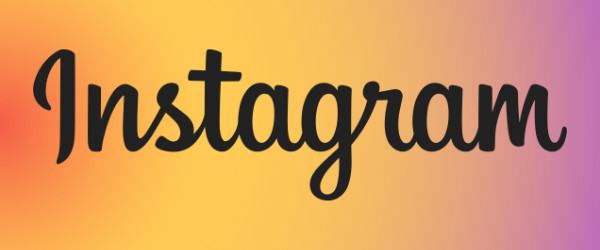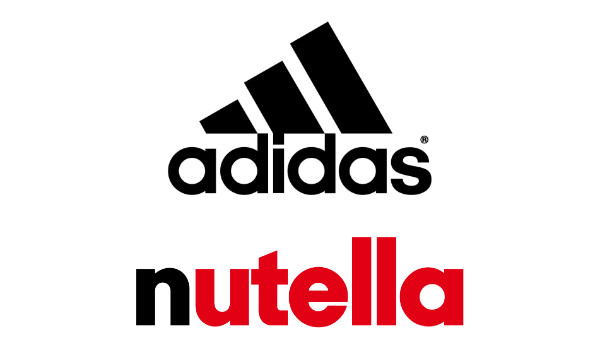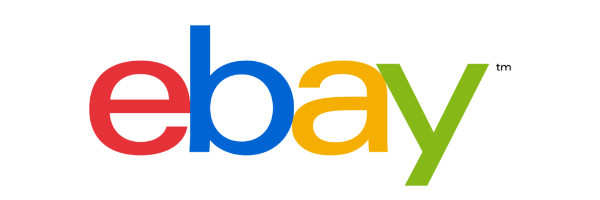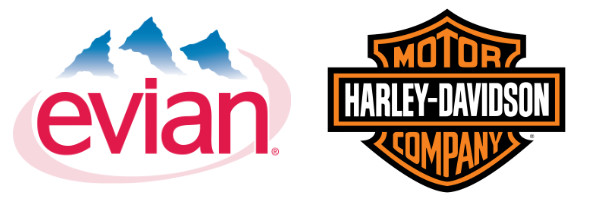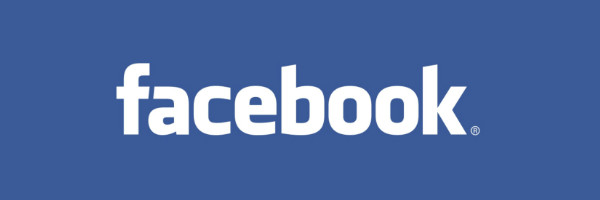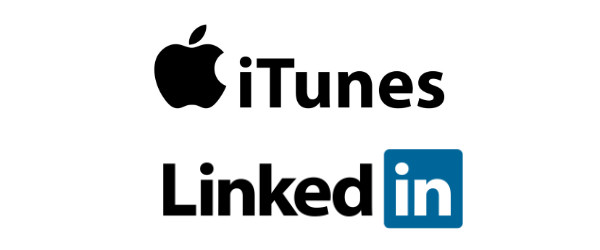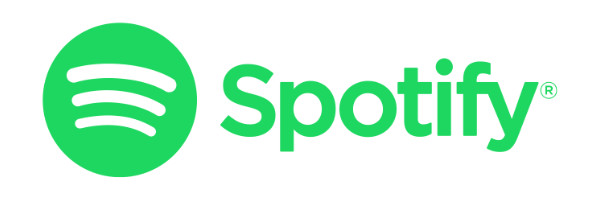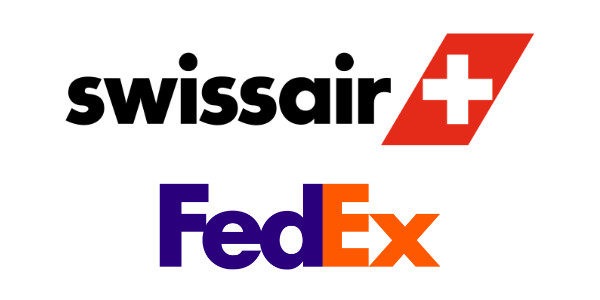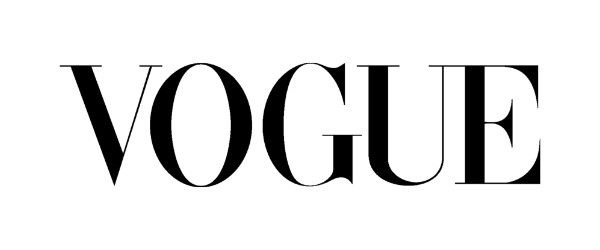
Les typographies de 15 logos célèbres
De nombreuses marques incorporent du texte à leur logo, que ce soit pour leur propre nom ou pour leur slogan. Le choix de la typographie doit donc être mûrement réfléchie.
Si vous êtes en manque d’inspiration ou si vous voulez rendre hommage à une marque que vous aimez tant, alors vous tombez bien. Car je vais vous révéler dans cet article les typographies utilisées par 15 marques connues.
La typographie manuscrite Billabong rappelle souvent la plage, le soleil et le surf.
Devenue célèbre grâce à Instagram, cette police est idéale pour donner un look à la fois vintage et élégant à votre logo.
Typographie géométrique sans empattement, la police Avant Garde Gothic semble être construite à partir de cercles et de lignes droites.
C’est une référence chez les graphistes qui aiment l’utiliser pour de courts blocs de textes.
La police d’écriture Bodoni a fait surface à l’époque où les designers expérimentaient le contraste entre les caractères épais et fins.
Cette typographie est idéale pour les marques de mode.
Futura a certainement été la typographie la plus utilisée au cours du 20ème siècle, les lettres géométriques donnant un look moderne.
Vous pouvez utiliser cette police d’écriture si vous souhaitez que votre marque soit reconnaissable à l’international.
Klavika a vu le jour en 2004 et se trouve aujourd’hui sur l’un des logos les plus connus au monde.
Cette police sans empattement et dotée de petites majuscules reste facilement identifiable. Vous pourrez l’utiliser sur votre logo pour mettre en valeur le nom de votre entreprise.
Créée en 1992, la typographie Myriad est très vite devenue populaire. Cette famille de police comprend plusieurs largeurs et les caractères se veulent nets, bien dessinés avec des crénages étendus.
Vous pouvez utiliser cette police d’écriture pour offrir au texte de votre logo une bonne lisibilité.
De nombreux logos utilisent le Helvetica, et pour cause : cette typographie se veut simple et utilitaire.
Cette police ayant fait ses preuves, pourquoi ne pas l’utiliser pour donner un look familier à votre logo auprès de vos nouveaux clients ?
Créée en 2005, la police d’écriture Proxima Nova allie typographie géométrique (Futura par exemple) et modernité.
Considérez cette police si votre marque est fortement connectée aux médias sociaux ou alors si vous souhaitez une présence moderne sur internet.
La typographie Univers comprend un large choix de largeurs et de positions pour les caractères. Son créateur Adrian Frutiger accorde d’ailleurs à cette police « une sensibilité visuelle entre les traits fins et minces, évitant ainsi une géométrie parfaite ».
Si votre logo a l’intention d’être diffusé à l’international cette typographie sera un très bon choix.
Pour la petite histoire, Garamond est devenue l’une des typographies les plus connues lorsqu’elle fût présentée en 1900 à un salon à Paris.
Cette police d’écriture se veut élégante et sophistiquée.
Garamond saura donner un look professionnel et intemporel à votre logo.
Perçu un temps comme un concurrent de la police Helvetica, la typographie Trade Gothic est à la fois simple et moderne.
Elle trouvera sa place sur des logos devant être affichés sur le web et où l’espace est limité pour le contenu textuel.